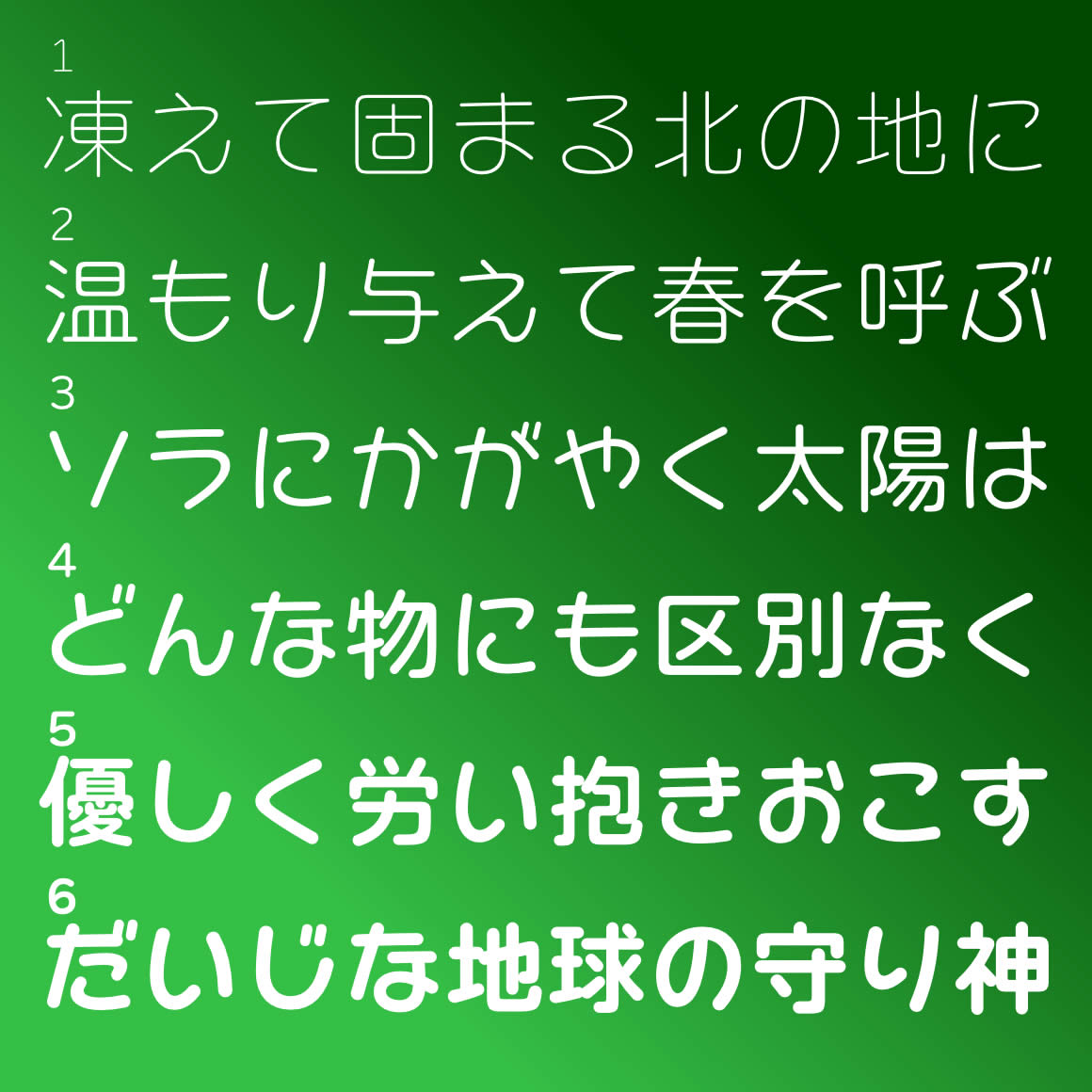
デザイン 若い人たちに人気の丸文字風かな書体「キャピー」と、
プレーンなイメージの丸ゴシック書体「レラ」を組み合わせました。
女性や若い人達に好まれるかな文字と、落ち着いた雰囲気の漢字を組み合わせたことで、どんな文章でも楽しく読みやすいイメージに変化します。
等幅バージョンは、英大文字のアイ「I」と英小文字のエル「l」数字のいち「1」や、英大文字のオー「O」と数字のゼロ「0」が、はっきり区別がされているので、URL表記やプログラム編集などにぴったりです。
連想されるイメージ
寄せられたコメントから抜粋
カワイイ・柔らかい・やさしい・いきいき・リズミカル・さっぱり・スッキリ・読みやすい・ニッコリ・新鮮・ほのぼの・しつこくない・楽しい・親しみがもてる・愛嬌がある・お洒落・ポップ・手書き風・遊び心がある・おちゃめ・シンプル・温かい・バランスが良い・心地よい・明るい